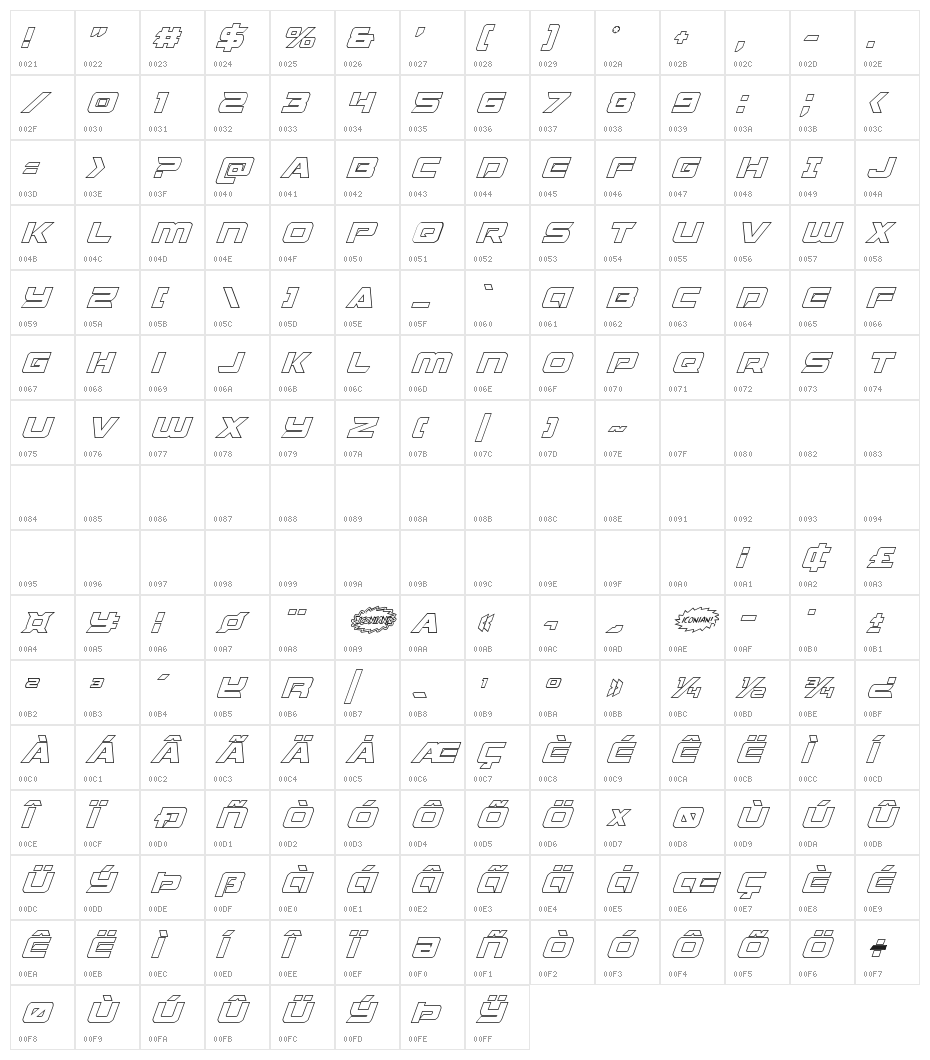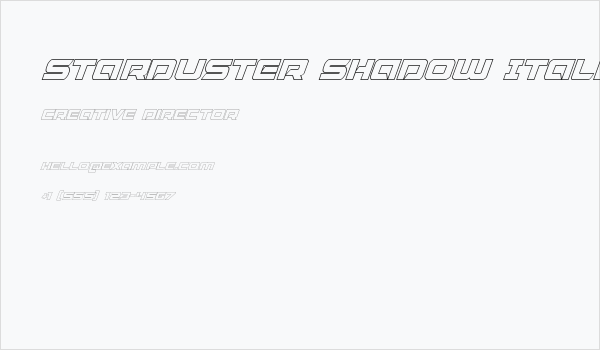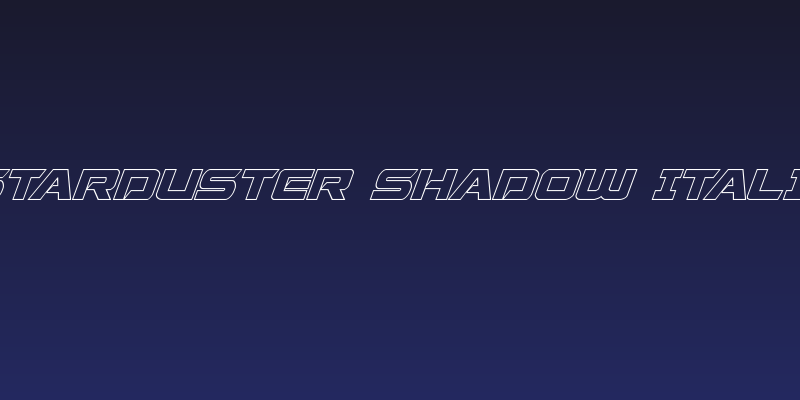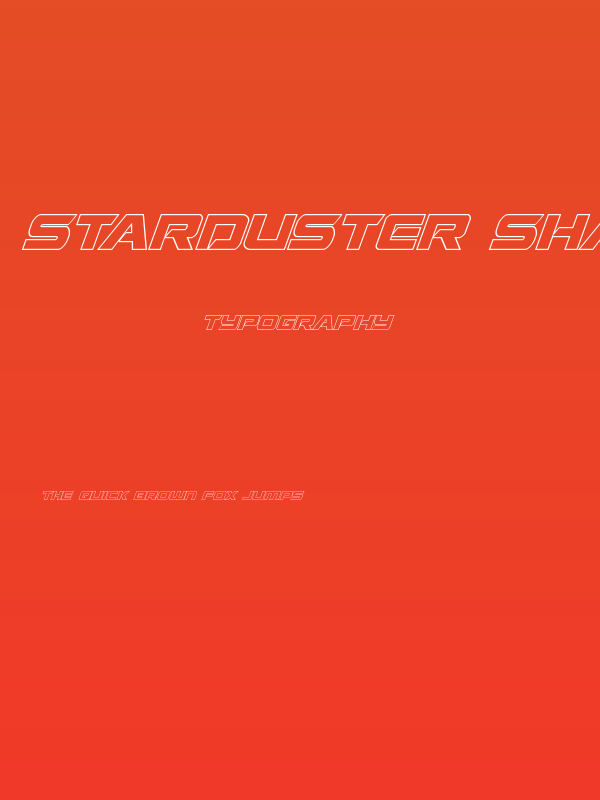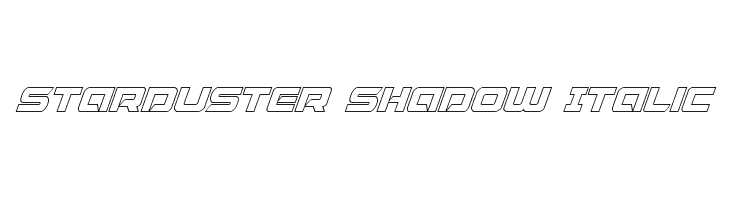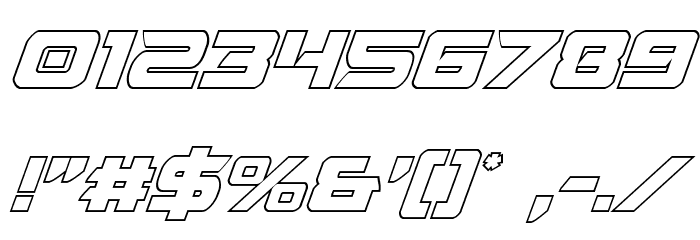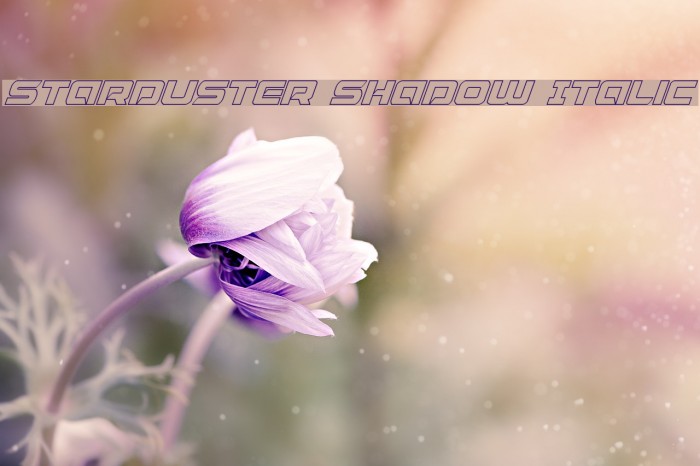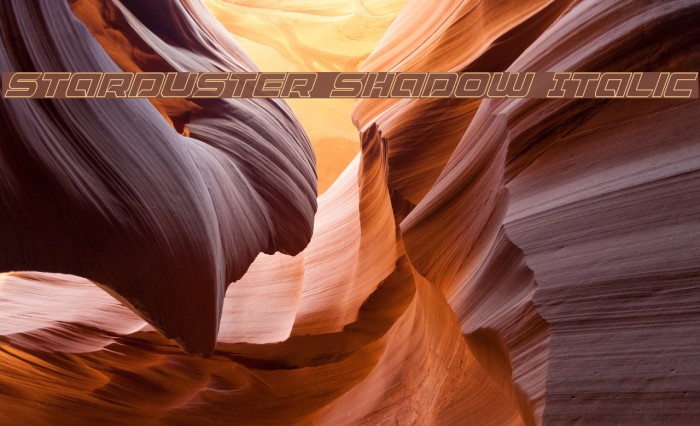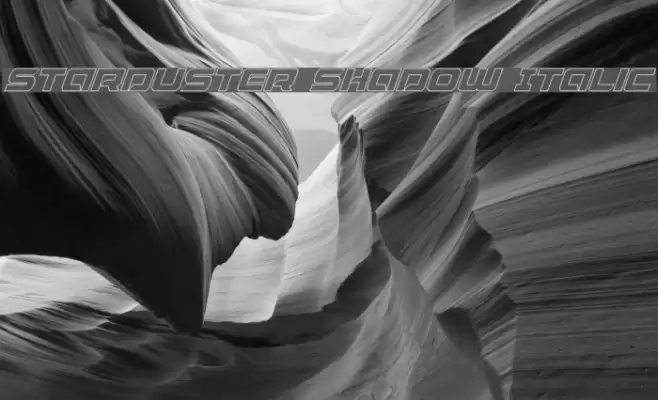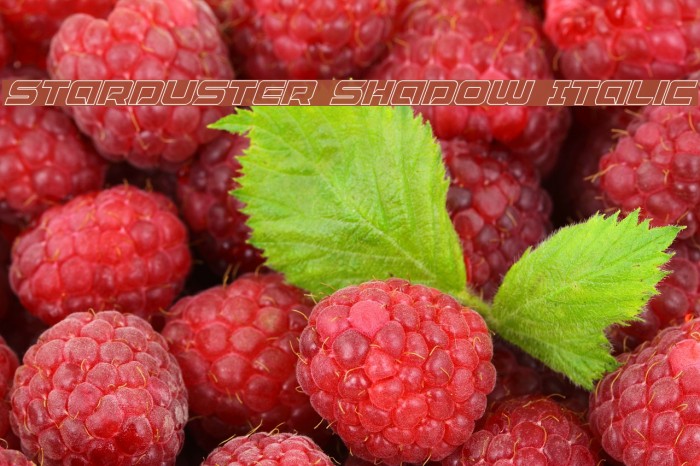
Starduster Shadow Italic Font
| Projetos propostos | Ideal for sci-fi themed projects, video game titles, posters, and branding that requires a modern and edgy look. |